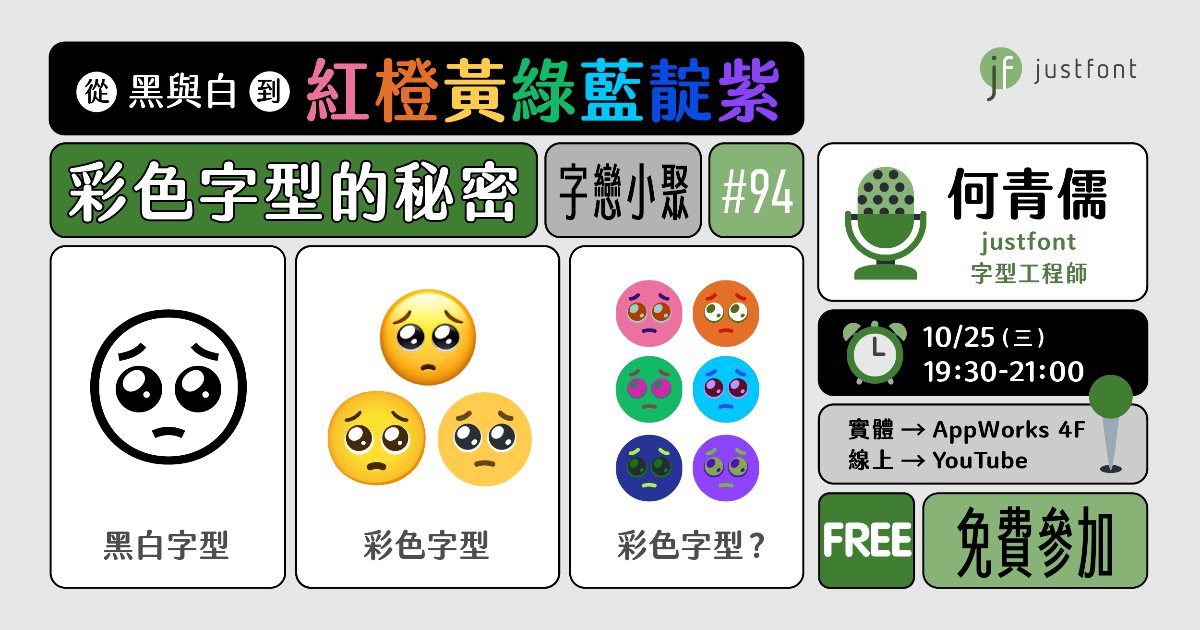
字戀小聚 #94|從黑與白到紅橙黃綠藍靛紫——彩色字型的秘密
字的世界,原本只有黑與白,直到彩色字型(color font)的出現⋯⋯
☄️💫🤯
老實說,也不是什麼超級新的技術 🙅🆕
最常見的彩色字型就是彩色 emoji 比如 ❤️💙💜💛🧡💚🤎🖤🤍♥️
justfont 做過的麥當勞薯條體跟麥克雞塊體也是彩色字型 🍟
但你聽過字型工程師介紹彩色字型嗎👂
彩色字型怎麼做的?
彩色字型自己可以做嗎?
彩色字型的顏色可以改嗎?
彩色字型可以用在網頁上嗎?
彩色字型可以⋯⋯
各種彩色字型的疑問🙋
由人稱 儒哥(尊稱)的字型工程師何青儒為您帶來——🎁
彩色字型的秘密🌈🔠🙊